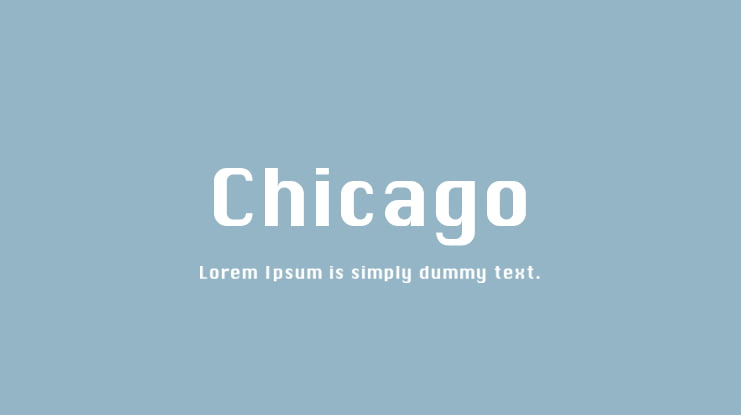
Tác giả: Susan Kare
Ngày phát hành: 1984
Ngôn ngữ: Tiếng Anh
Bộ Font: Chưa rõ
Phân loại: Đơn giản
Được thiết kế vào những năm 1930, Font Chicago đã trở thành một biểu tượng trong thế giới của đồ họa và thiết kế. Font chữ này, thuộc bộ font chữ không chân mang nét chữ vuông vức, mạnh mẽ và đầy cá tính mang đến một phong cách độc đáo và dễ nhận diện, phù hợp với các ấn phẩm in ấn cần sự nổi bật và ấn tượng. Font Chicago nổi bật với các ký tự đậm, rõ ràng và dễ đọc, ngay cả trên màn hình có độ phân giải thấp và nó đã trở thành một phần không thể thiếu của hệ điều hành Macintosh cổ điển, được sử dụng trong các giao diện như System 7 và các phiên bản đầu của Mac OS.